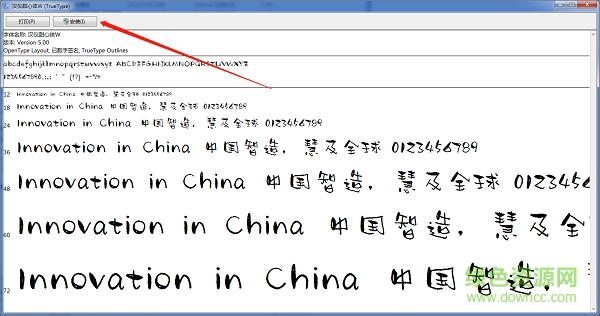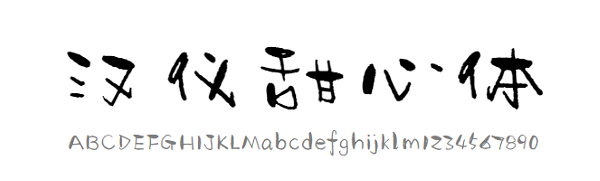
漢儀甜心體是漢儀字體最新發(fā)布的一款簡單優(yōu)雅又具有童趣的手寫字體,字體筆畫有粗有細(xì),簡單的拼湊讓整體看起來更加的舒適,同適用于日常寫作之中,喜歡的用戶快來綠色資源網(wǎng)下載吧!
漢儀甜心體W是漢儀字庫設(shè)計(jì)的一款非常個(gè)性的字體,并在七夕節(jié)發(fā)布,這款字體略帶搞笑的氣息,有的筆畫粗,有的筆畫細(xì),但是每一個(gè)筆畫都不規(guī)整,休閑程度比較高,如果用在非常甜蜜的文字上面,效果非常好,不僅適合情人之間使用,同時(shí),也適合情人節(jié)做宣傳使用!
1、支持簡體中文和繁體中文。
2、支持網(wǎng)絡(luò)常用中文簡繁。
3、支持西文和數(shù)字。
4、字體風(fēng)格:時(shí)尚、現(xiàn)代、可愛、快樂、浪漫、女性、手寫風(fēng)、溫柔、休閑、優(yōu)雅、有趣
5、推薦場景:標(biāo)志、廣告、屏顯、書籍、影視、游戲